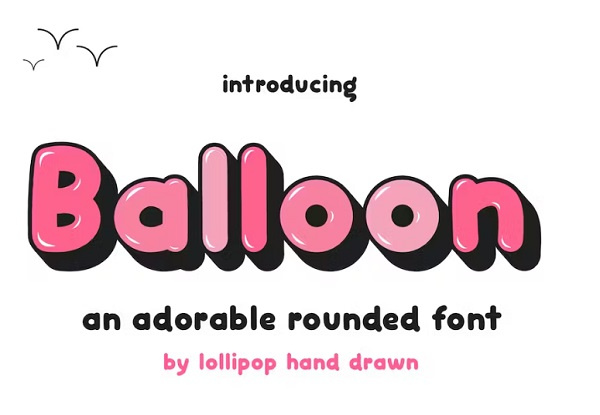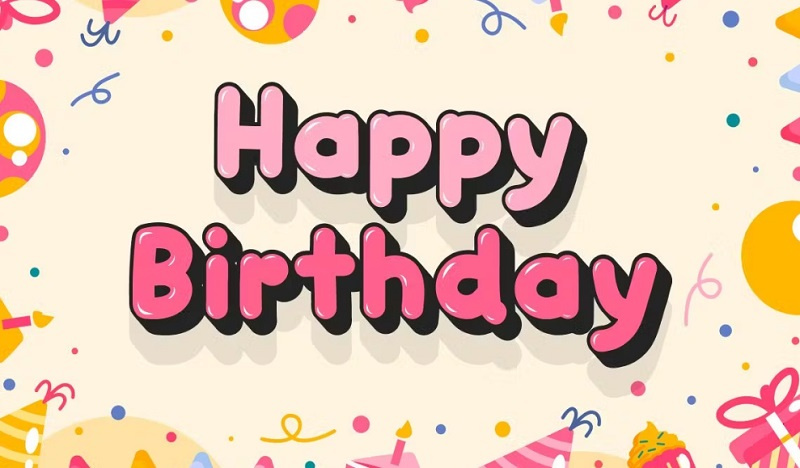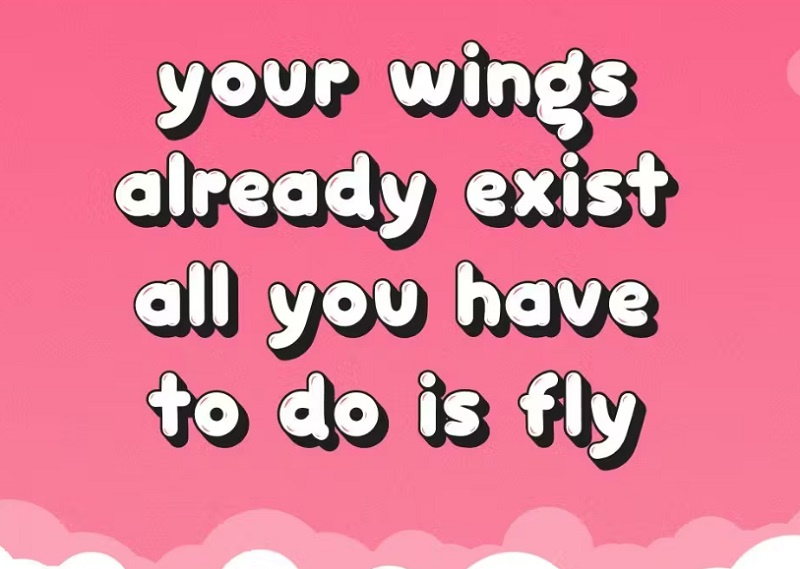
دانلود فونت انگلیسی بادکنکی از جی اف ایکس دانلود. این فونت انگلیسی با طراحی بسیار زیبا به سبک بادکنک می باشد. از این فونت انگلیسی بادکنکی برای طراحی های کودکانه، کارتونی، برندسازی، طراحی های تبلیغاتی، طراحی لوگو و ... می توانید استفاده کنید. در ادامه با دانلود این فونت زیبا و مشاهده تصاویر آن از gfxdownload.ir با ما همراه باشید.
دانلود فونت انگلیسی بادکنکی کودکانه